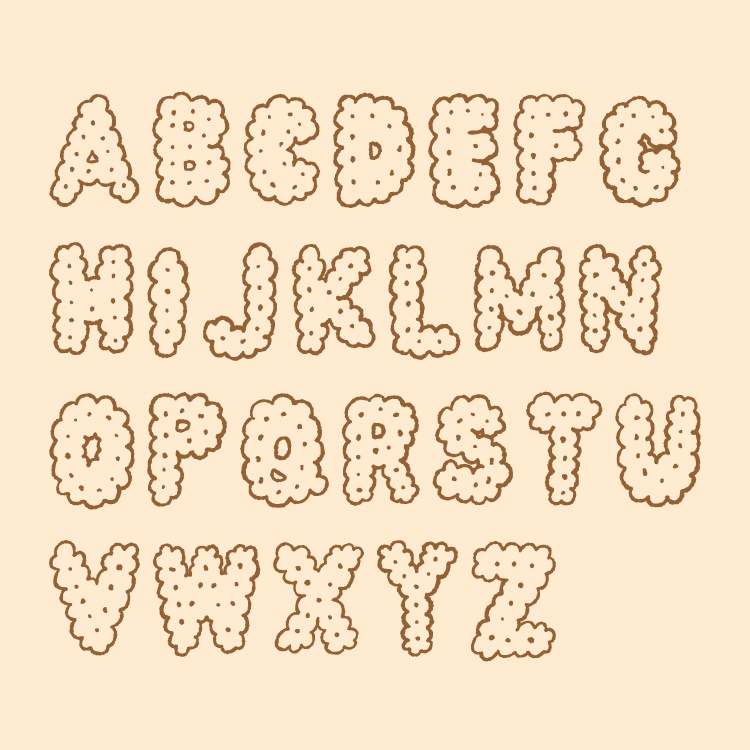
ビスケットフォント フリー版
ビスケットみたいな手描きフォントです。 アウトラインのフォントと、ベースのフォントの二種類が入っています。ベースのフォントにグロー加工をして重ねて使用するとサムネイルのような表現ができます。アウトラインの方をそのまま使ってもかわいいですよ。 - biscuit_lite.otf - biscuit_base_lite.otf - readme.txt ライト版は大文字のみ。 WINDOWSで作成したOTF(マックの動作確認はしていません) ----- It's a hand drawn font that looks like a biscuit. Includes two types of outline fonts and base fonts. If you apply glow processing to the base font and use it repeatedly, you can create a thumbnail-like expression. It's cute even if you use the outline as it is. Lite version is upper case only. OTF created on WINDOWS (not tested on Mac)